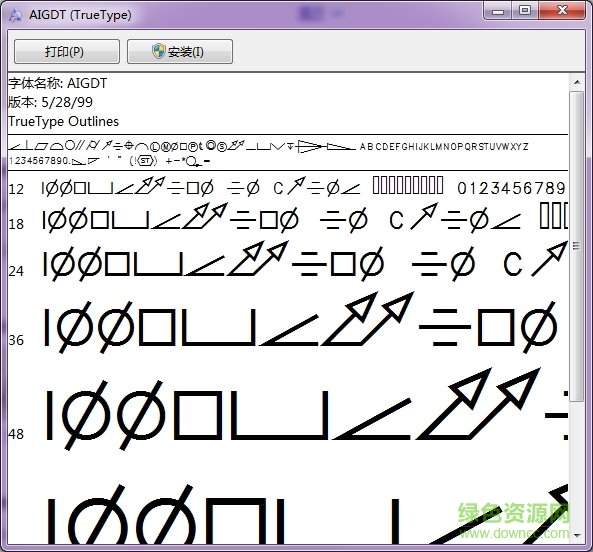
aigdt字體是一款非常特殊的英文系統(tǒng)字體,不支持中文書寫,文字就是各種符號形式,但可以用來表達cad字體,如果你感興趣,就來綠色資源網(wǎng)免費下載吧!
AIGDT、AMGDT、GDT 數(shù)學角度、圖形符號,如平行四邊形符號,它將許多字母渲染成各式各樣的符號,用途十分廣泛。字母數(shù)字從0到10的序號,多種記號和問嘆號,幾個幾何形狀和星形。